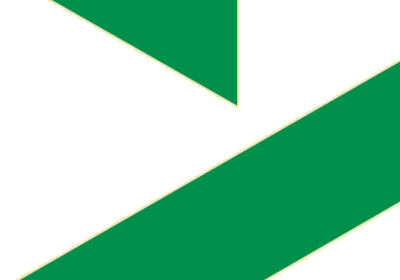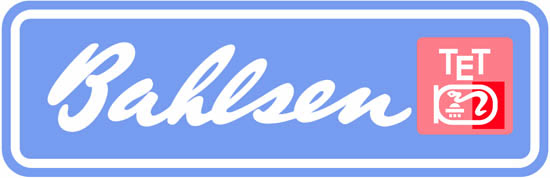
Neue Runde Typo-Quizz gefällig?
Also ich sehe da den Schattenriss zweier Bäume am Horizont. Wer da Serifen sieht, ist doch Typo-geschädigt! :D
ging mir auch erst so.
vielleicht gibts ja doch noch eine chance für uns. ;)
daß wird schwierig; rote Bäume mit weißem Hintergrund ... als Schatten ..? Ganz klarer Fall - psychiatrische Wohngruppe! Verlust der Eigenwahrnehmung und Fremdwahrnehmung - könnte man noch fragen, wie es denn mit der Orientierung zur Zeit, zum Ort und zur Person aussieht .. aber da will ich in anbetracht der Uhrzeit nicht mehr hinterfragen..
Ich sehe darin nichts anderes als zwei Gläser! Ein Weinglas und einen Cognacschwenker oder so. (Obwohl ich eher Antialkoholiker bin...)
FaberCastell.
Die Turnierritter überm C.
Würde als Beleg ja gern meine Polychromos-Schachtel auf den Scanner legen, aber dann fallen alle 120 Stifte :D heraus ...
Ich geh mal davon aus, dass ich richtig liege. Also: Welche Traditionsmarke verbirgt sich hinter diesem Detail?
Hat das Detail vielleicht hiermit was zu tun?
Im Jahre 1904 hatte Bahlsen die Idee, seine Cakes mit einer altägyptischen Hieroglyphe zu versehen: »dschet" gesprochen (vereinfacht "tet" geschrieben) ...
Falls es stimmen sollte, mach ich hiermit weiter, falls nicht, sofort löschen.
Diesen wahnsinnigen Extrem-Expert-Level-Ausschnitt lasse ich nur kurz stehen, das kann keiner herausfinden, oder etwa doch?
Das, das, das, ich fang schon an zu stottern, gibt’s doch gar nicht.
Unglaublich, herzlichen Glückwunsch!
Hat das Detail vielleicht hiermit was zu tun?
Im Jahre 1904 hatte Bahlsen die Idee, seine Cakes mit einer altägyptischen Hieroglyphe zu versehen: »dschet" gesprochen (vereinfacht "tet" geschrieben) ...
Das war - natürlich - richtig.
Chapeau.
Deutscher Fußball-Bund?
In der Tat. Ich hielt das für schwerer.
War nicht sooo schwer, weil heute alle Medien vom Bundesligastart überquellen. UND: ich bin kein Fußballfan. Tja.
Jau, ist richtig. War doch zu leicht....
Janek: Du bist dran!
Jau, ist richtig. War doch zu leicht....
naja, ich grase hier mal die einfachen ab, wenn alle anderen offline sind :-) steigert das selbstbewußtsein ...
also dann: neues spiel, neues glück:
erwarte "sportlichen" ehrgeiz ...
Das ist St. Pauli, meine ich, denn die haben nicht etwa den Totenschädel, wie zu vermuten, sondern die Hammaburg (das "Hamburger Tor") mit den Sternen über den Türmen im Wappen. Da brauch ich bloß auf mein "Retter"-T-Shirt zu gucken :D
sauber, herr pautner.
aber als münchner ein retter-shirt ... :wink:
bin mir übrigens nicht ganz sicher, ob der totenkopf (jolly roger) nicht als offizielles logo neben dem gezeigten steht. dachte, ich hätte sowas mal gelesen. kann ich aber recherchieren, mache eh gerade eine arbeit über den verein.
demnach: it's your turn!
Also gut, auf ein Neues:
"LO" :?:
... ja, "LO", aber das ist noch nicht alles.
mmmmmh, mich erinnert das ganz stark an ein bekanntes popart-plakat (glaube ich). darauf ist das wort "LOVE" mit schrägem "O" gesetzt.
aber gibt's das als logo?
und waren die 4 flächen hinter den buchstaben nicht in unterschiedlichen farben gesetzt?
oder erzähle ich gerade schwachsinn :oops: ?
ich rätsel weiter ...